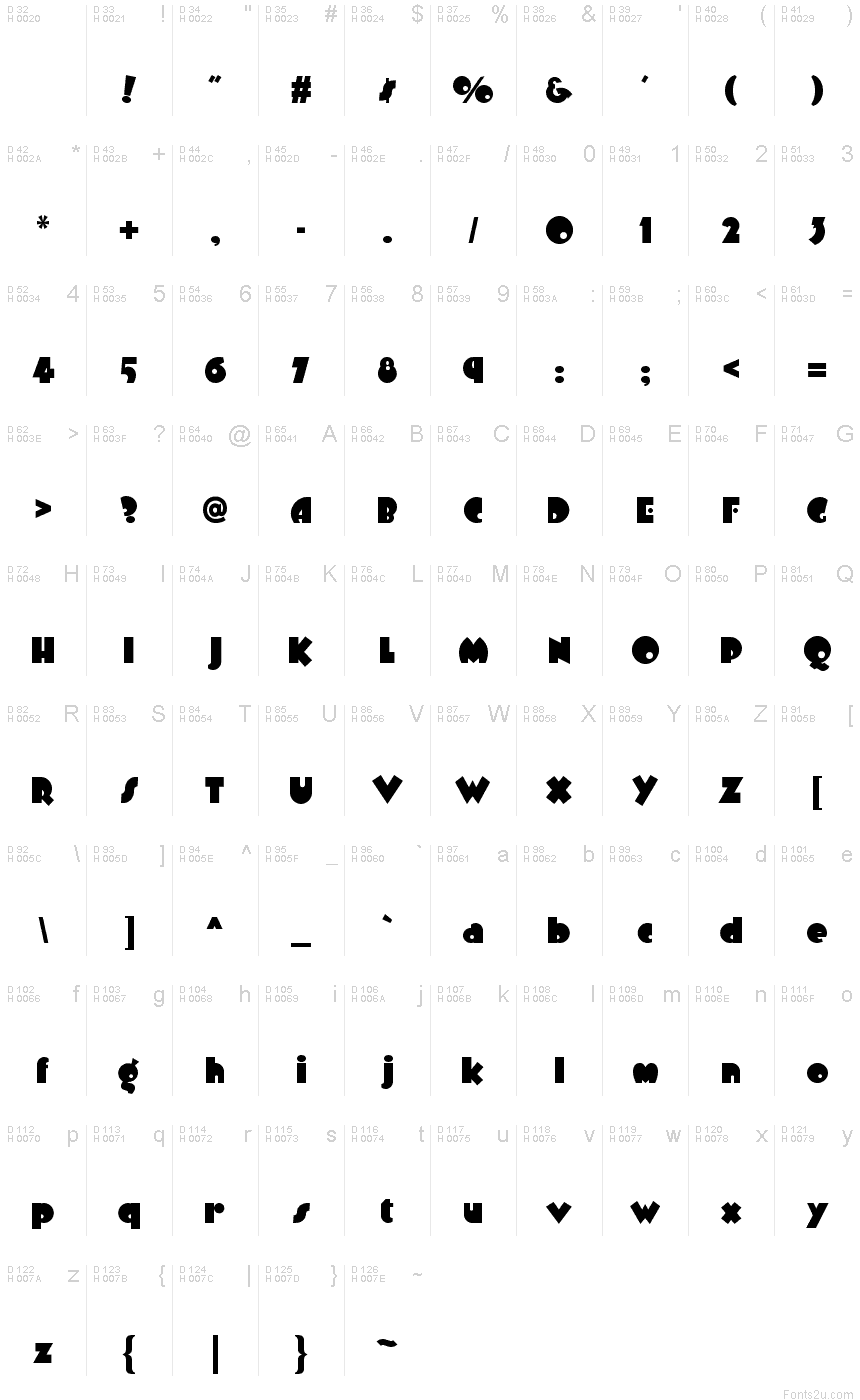
Arbuckle Remix autorstwa Nicka Curtisa to darmowy, retro krój typu display, nawiązujący do ciężkiego stylu witryn sklepowych z lat 70. Litery zbudowane są z wyrazistych geometrycznych kształtów i głębokich łuków, dzięki czemu czcionka jest jednocześnie zabawna i masywna. Okrągłe kropki i zaokrąglone łączenia nadają jej miękki, niemal klockowy rytm.
Idealnie pasuje do plakatów, okładek płyt, identyfikacji kawiarni, etykiet, kart tytułowych oraz dużych nagłówków redakcyjnych, gdzie potrzebny jest natychmiastowy klimat tamtych lat. Użyj Arbuckle Remix, gdy chcesz, aby krótkie słowa lub inicjały wyglądały odważnie i przyjaźnie – te przysadziste łuki i przerysowane, okrągłe formy błyskawicznie wykonują kawał dobrej wizualnej roboty.